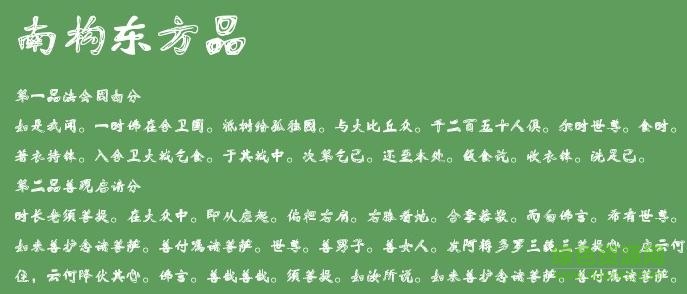
南構(gòu)東方品字體
南構(gòu)東方品字體是南構(gòu)字庫(kù)出品的最新手寫字體,采用手繪的方式寫成,具有立體感,適用于藝術(shù)創(chuàng)作、海報(bào)設(shè)計(jì)等方面,歡迎大家來(lái)綠色資源網(wǎng)踴躍下載使用!
南構(gòu)東方品字體是一款手繪風(fēng)格的字體,字里行間都透露出一種自由奔放的筆觸感。